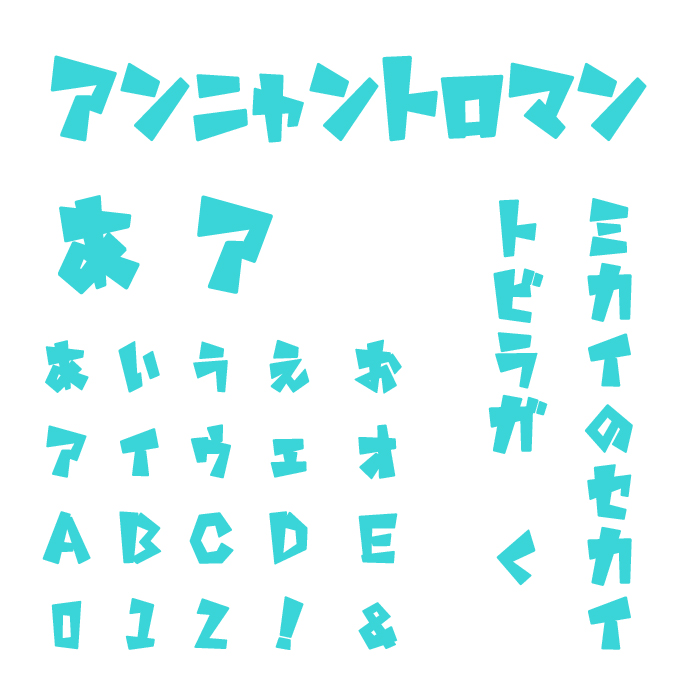
「アンニャントロマン」フォントは、強烈なポップで個性的で、ロゴデザインの主役として多くのクリエイターから人気のあるデザインフォントです。
組むだけでロゴのようになるフォントとして、ロゴ向けフォントとして制作されているので、一文字ごとに表情が豊かで可愛らしいフォントとなっています。
同人誌やゲームのクリエーターたちに重宝されており、勢いあるデザインが個性豊かで人気あるフォントです。ベタ打ちしたままで使用しても、ロゴとして使えたり、少し加工するだけでも印象が変わります。(フォント配布サイトのサンプルを掲載しています。)
斜体にしたり、立体感を出すことで、さまざまなバリエーションのロゴを演出することが可能です。文字それぞれが、もともとポップでダイナミックな雰囲気を持っているため、さまざまなシチュエーションピッタリなフォントです。
アンニャントロマンフォントの文字見本
収録文字は、ひらがな、カタカナ、英字、記号の一部が収録されています。